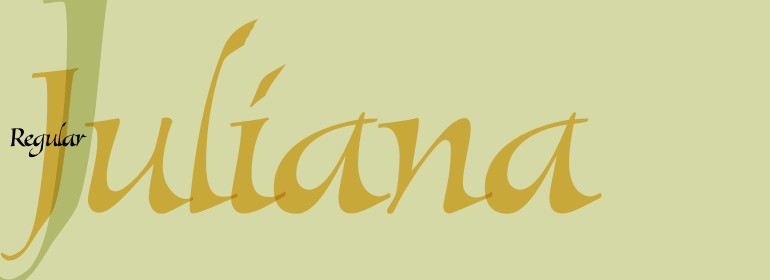
Juliana™
Juliana™,这款字体结构工整、笔画清晰,兼顾美观与易读性,适用于标题、正文、海报、包装、LOGO 等多种场景。字形优雅稳定,风格百搭耐看,适配日常排版与创意设计,让文字呈现更舒适、更具质感。Juliana™一笔一画,皆是细节,以均衡的比例、流畅的线条打造舒适视觉体验,字形端正大气,风格简约现代。无论是商业设计、品牌宣传还是日常排版,都能轻松驾驭,让文字更有格调与力量。Juliana™字体下载。
字体品牌: ITC(Monotype) 设计师:Bouwsma,Philip 字体分类:书法体 字体属性:外文 字符集:Unicode 发布时间: 2018